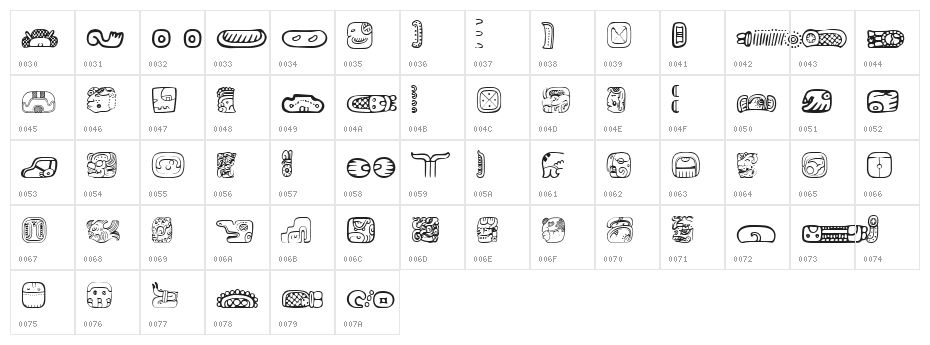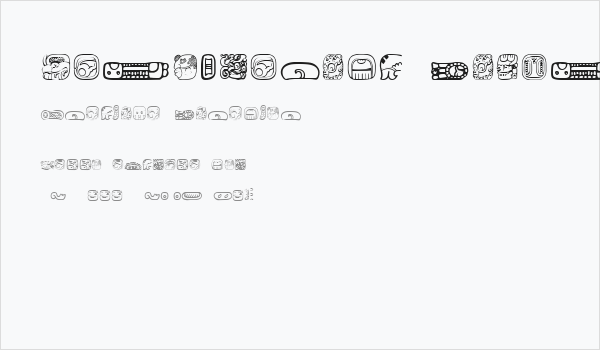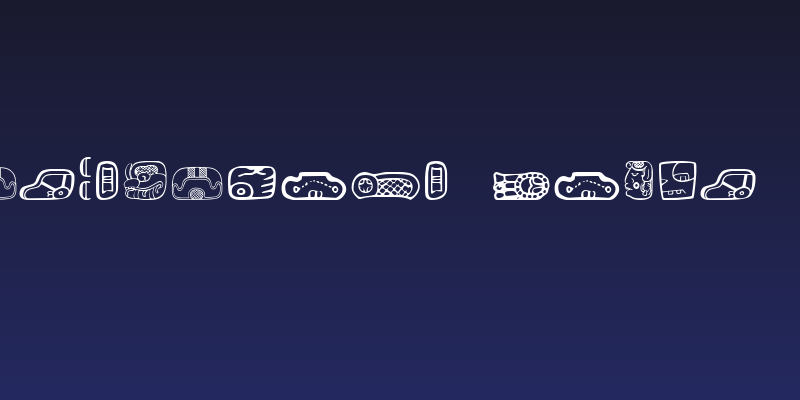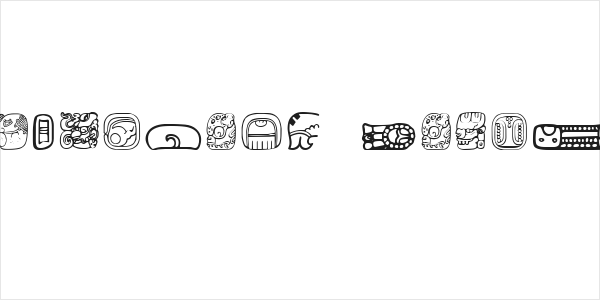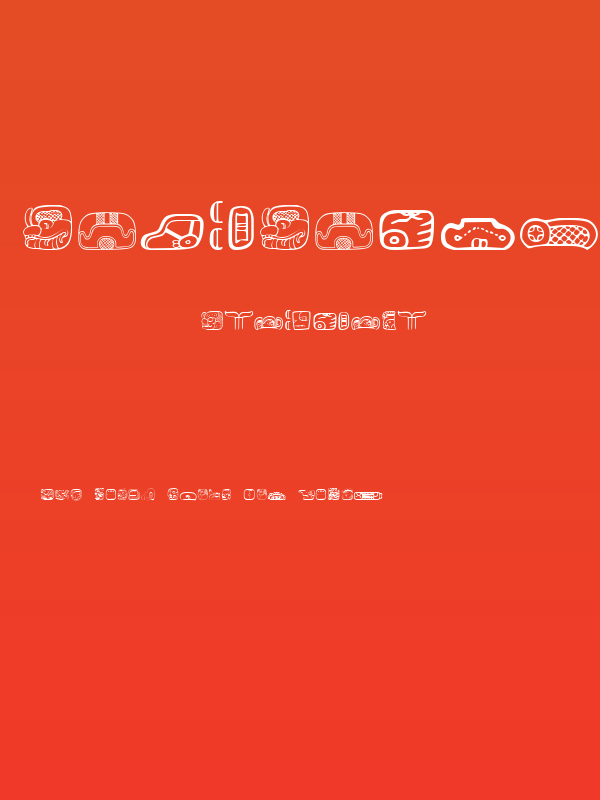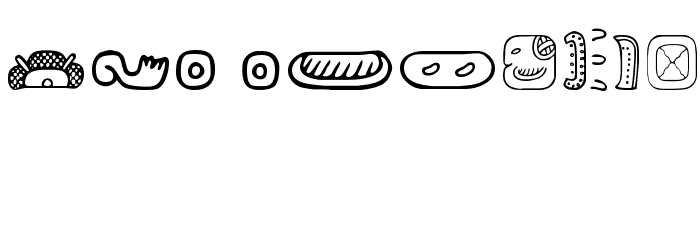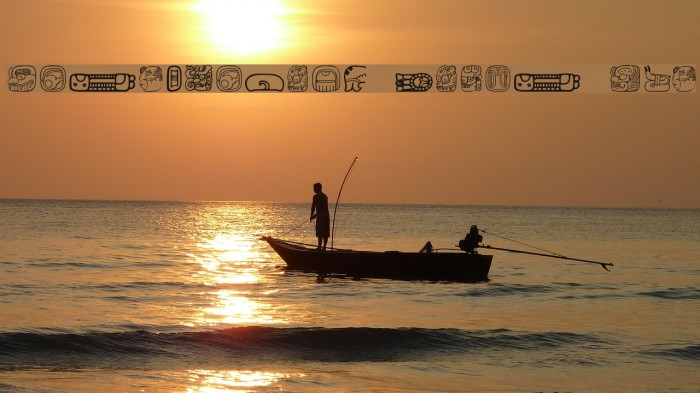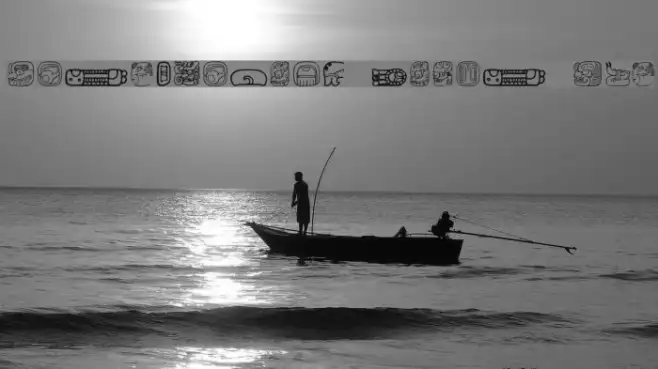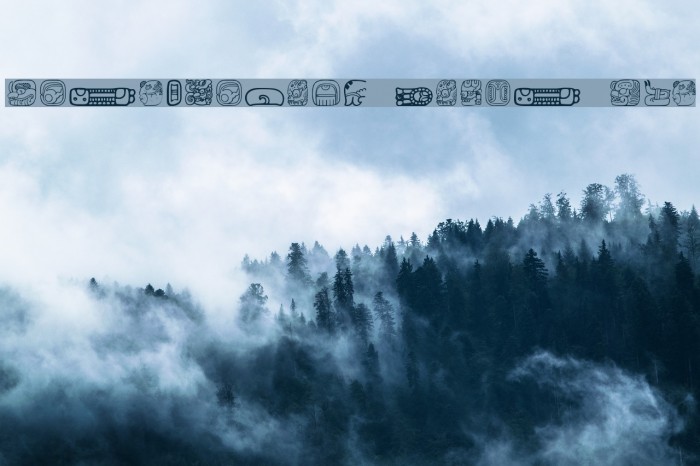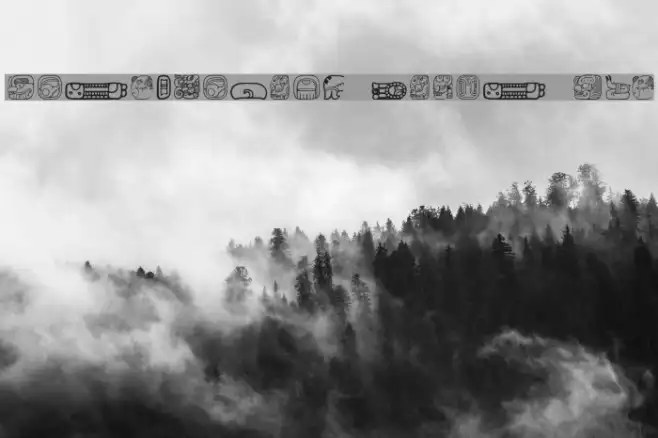
MesoAmerica Dings Two Font
| Caso d'uso | Logos, Posters, Artistic Designs |
| Progetti proposti | Ideal for cultural exhibitions, historical presentations, themed event posters, and artistic designs that require a touch of ancient mystique. |